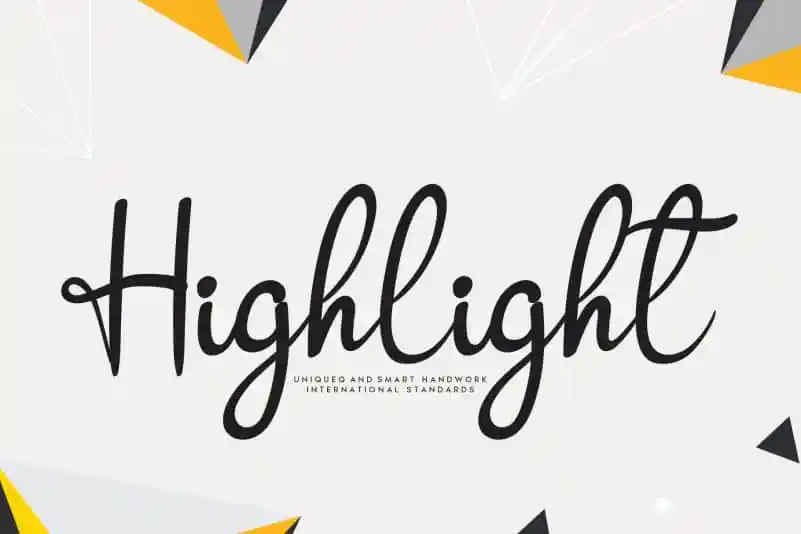
Highlight Script Font – Download Grátis
A fonte ‘Highlight Script Font’ é uma criação única e criativa produzida pelo designer andikastudio para você. Nesta categoria de fóruns de escrita à mão, a ‘Highlight Script Font’ oferece um gosto autêntico que vai além do simples uso estético. Ela traz uma experiência visual notável, com linhas elegantes e detalhes únicos que permitem criar textos que chamam atenção. Para designers apaixonados por personalização de texto, este é um recurso precioso. A ‘Highlight Script Font’ transformará seu design e aumentará o impacto do seu trabalho. Sua utilização em anúncios, cartazes ou editoriais pode fazer uma grande diferença na comunicação visual. Obrigado a todos que buscam inspiração para seus projetos!